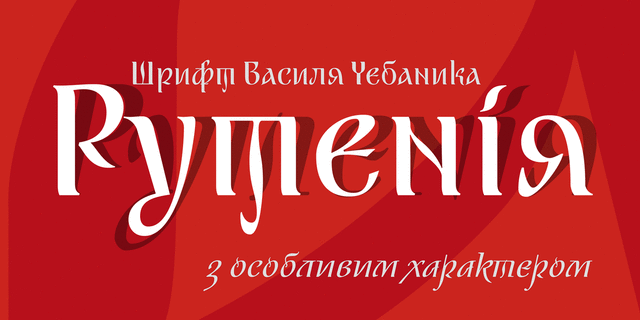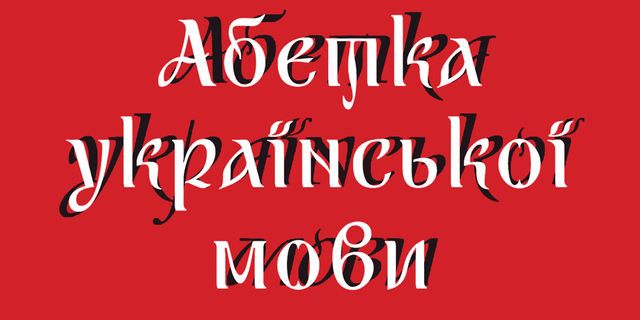
Изысканный шрифт Рутения (обновленный) в двух начертаниях является цифровой версией знаковой работы «Графіка української абетки» известного украинского каллиграфа и книжного графика Василия Яковлевича Чебаника. Прямое и курсивное начертания Рутении, прекрасно работают в акциденции и коротких текстах. Декоративность, выразительность и вариабельность помогут при создании логотипов. Некоторая торжественность и украинская окраска пригодятся для создания поздравительных открыток, дипломов, посвящений и благодарностей. Расширенная латиница и стандартная (современные славянские языки) кириллица позволят оформлять тексты на десятках языков. Этот шрифт уникален тем, что в нем Василий Яковлевич представил буквы украинского алфавита, максимально приближенные к первичным традиционным формам, которые были несколько искажены реформой Петра I, от чего нынешняя украинская кириллица имеет много некорректных и несуразных букв, хотя мы к ним уже привыкли. Например точечки вверху и внизу буквы О – это элементы, которые использовались в глаголице, предшествовавшей кириллическому письму.
Шрифт разработали Василий Чебаник, Виктор Харик и Геннадий Заречнюк в 2017 году. Обновленные версии с OpenType фичами и полужирные начертания созданы при технической поддержке Андрея Шевченко и Константина Головченко в 2019 году.